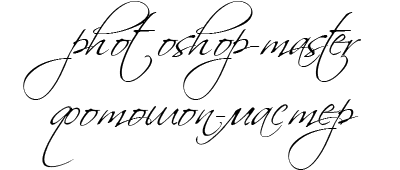
Отлично, пишет красиво! Благодарю!
Самый прикольный рукописный шрифт (по моему мнению):)))
Прикольный, но однотипный.
Обьясните пожалуйста, почему если он русифицированный, но хоть убейте на русском не пишет?
Долго искала,этот прекрасный почерк)
но на каких сайтах не лазела,не находила)
Помню у меня был такой пенал классный и там что-то было написано как раз этим шрифтом:D
Потрясающий шрифт!
Шрифт шикарный!
Замечательный шрифт. Спасибо огромное!
а мне не нра. если писать большой текст смотрится веревкой
красивый шрифт))
Какой шрифт **.
Какой шрииифт...